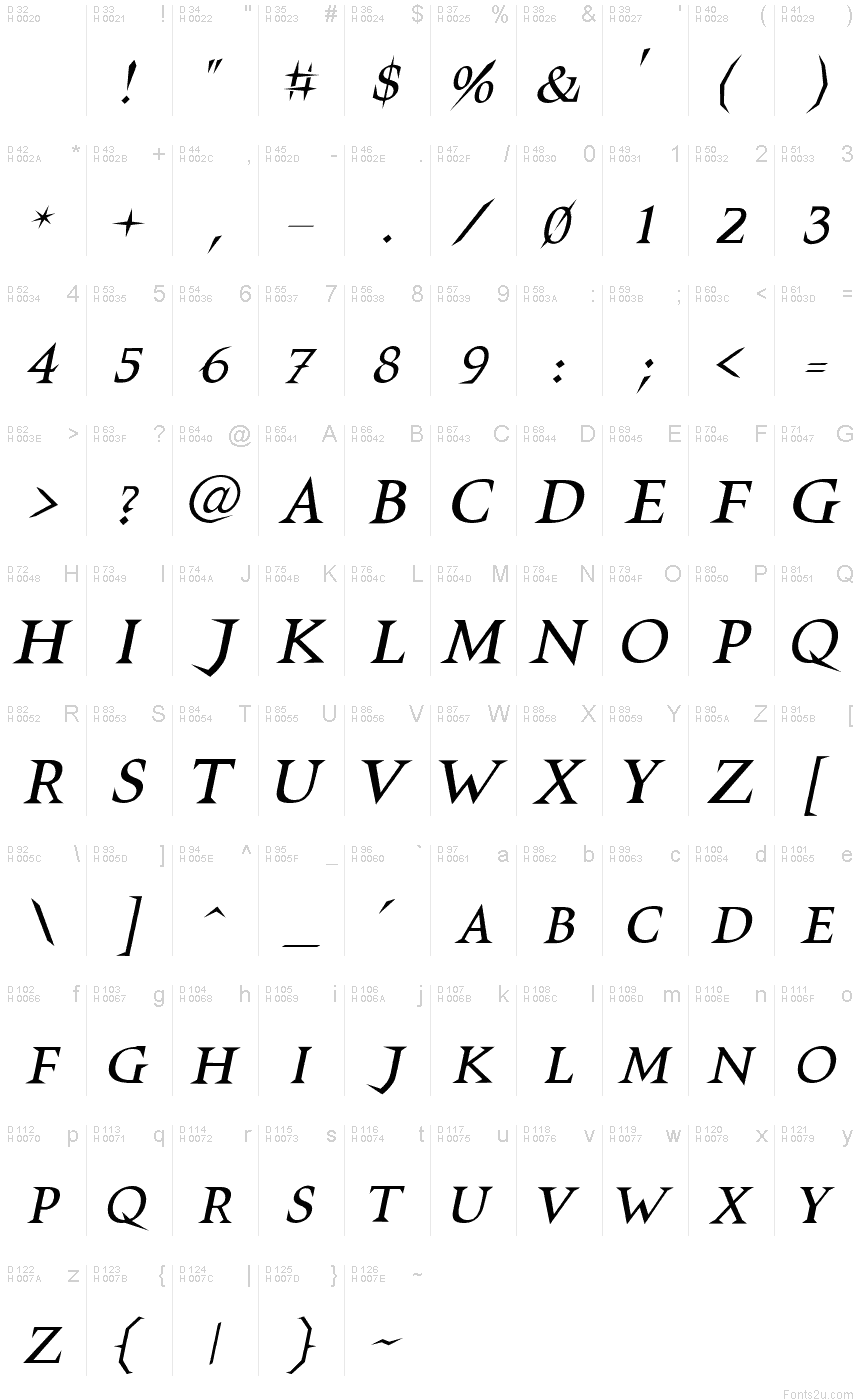
Podgląd czcionki VTCSwitchbladeRomanceItalic
VTC Switchblade Romance Italic od V.T.C. Vigilante Typeface Corporation to darmowy, retro font typu display, utrzymany w zmysłowym klimacie kieszonkowych wydań z późnych lat 60. Litery są mocno pochylone i ostro cięte, łącząc delikatne połączenia z szerokimi, rozkloszowanymi pociągnięciami oraz spiczastymi szeryfami, co nadaje całości dramatycznej, nieco niebezpiecznej elegancji.
Naturalnie odnajduje się w tytułach plakatów, na okładkach płyt, w brandingu butików, nagłówkach magazynów i planszach tytułowych filmów, gdzie odrobina melodramatu jest wskazana; jako darmowy krój, świetnie sprawdzi się również w inicjałach lub krótkich cytatach, które potrzebują tego ostrego jak nóż impetu. Wybierz go, gdy szukasz romansu z pazurem zamiast słodyczy, ponieważ pochylony rytm sprawia, że nawet kilka słów nabiera intensywnego wyrazu.